35 migliori font per loghi e come scegliere l'opzione migliore
Un logo deve comunicare molto con poco, e il font scelto svolge un ruolo cruciale. Sia che il tuo marchio sia divertente e accogliente, sia che sia elegante e professionale, il carattere tipografico giusto definisce il tono e lascia un'impressione duratura.
Creare un marchio forte con il font giusto
Font 1: Instrument Sans
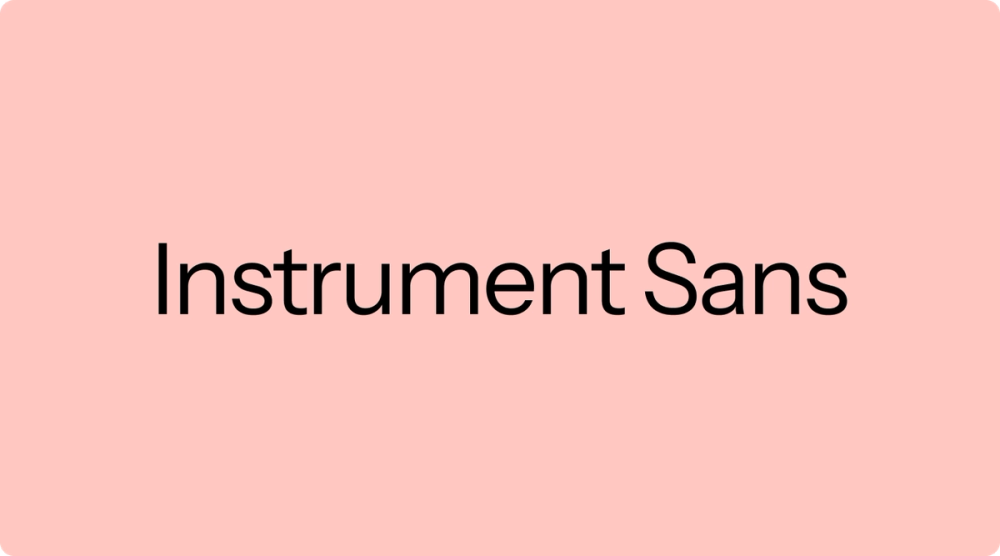
Tipo di font: sans serif
Instrument Sans è un font sans serif geometrico moderno con linee pulite e un design equilibrato. Porta un tono leggermente giocoso senza sacrificare la chiarezza, cosa che lo rende un'ottima scelta per i loghi che devono avere un aspetto attuale e trasmettere un senso di sicurezza.
Ideale per: startup tecnologiche, società di software e marchi moderni che desiderano un look elegante e professionale
Font 2: Instrument Serif
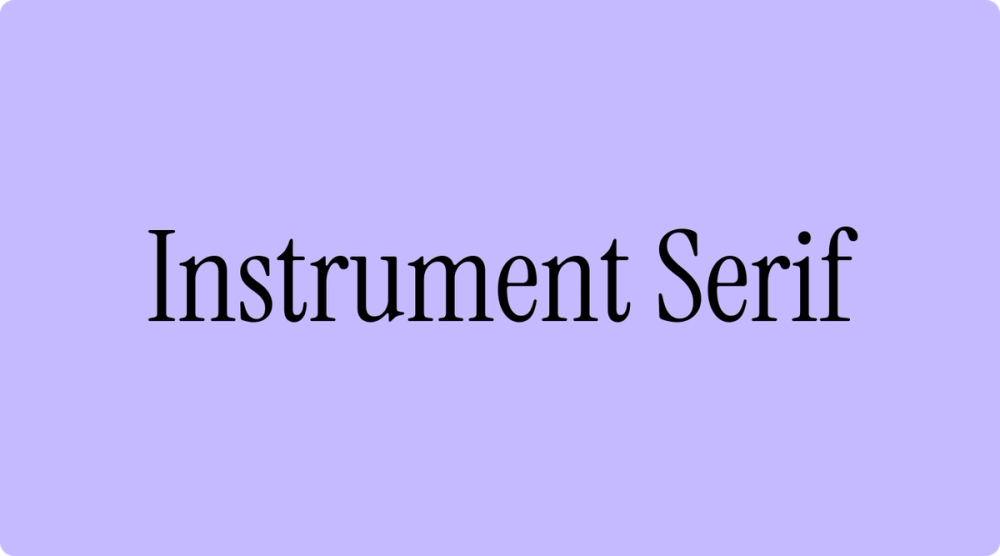
Tipo di font: serif
Instrument Serif unisce la classica struttura serif a un tocco raffinato e moderno. I suoi dettagli sottili aggiungono eleganza pur mantenendo un tono accessibile: l'ideale per i loghi che devono avere un look raffinato senza essere eccessivamente formali.
Ideale per: marchi di lusso, istituti finanziari e aziende di fascia alta che cercano di bilanciare raffinatezza e fascino informale
Font 3: Inclusive Sans
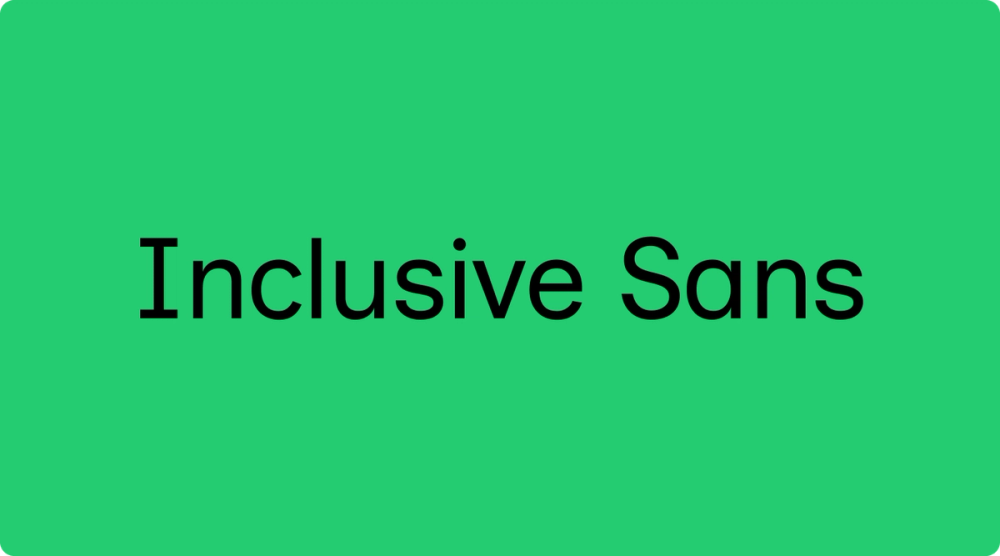
Tipo di font: sans serif
Inclusive Sans è stato progettato pensando all'accessibilità. Le sue forme aperte e la spaziatura generosa migliorano la leggibilità, rendendola una scelta affidabile per i loghi che danno priorità alla chiarezza e all'inclusione.
Ideale per:istituti scolastici, organizzazioni sanitarie, organizzazioni non profit e aziende che danno priorità all'inclusività e alla chiarezza
Font 4: Rethink Sans
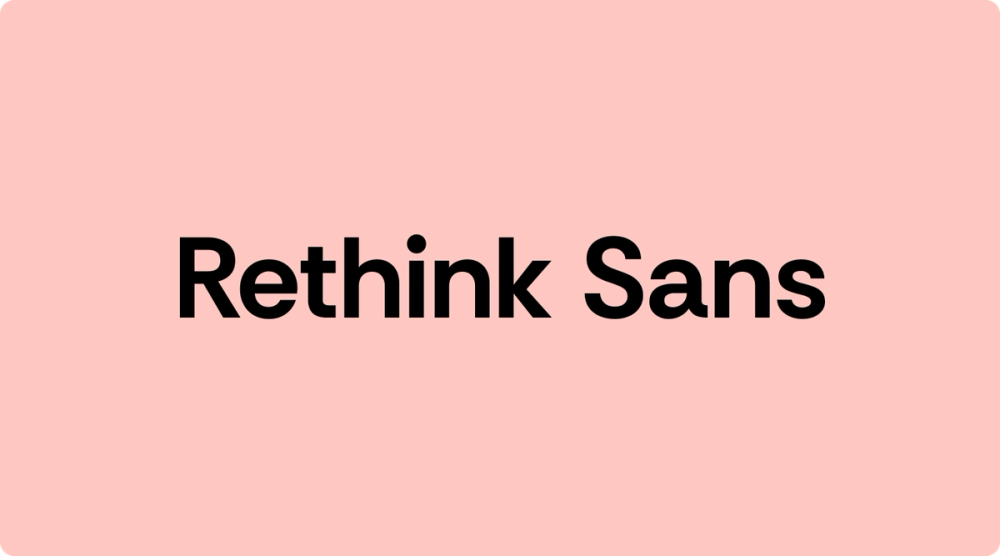
Tipo di font: sans serif
Rethink Sans trova un equilibrio tra audacia e semplicità, facendosi notare senza essere eccessivamente decorativo. Il suo design pulito e moderno lo rende ideale per i loghi che trasmettere un'immagine forte ma essere comunque accessibili.
Ideale per: agenzie creative, società di marketing e pubblicità, aziende tecnologiche e chi mira a una forte identità visiva pur mantenendo professionalità e calore
Font 5: Plus Jakarta Sans
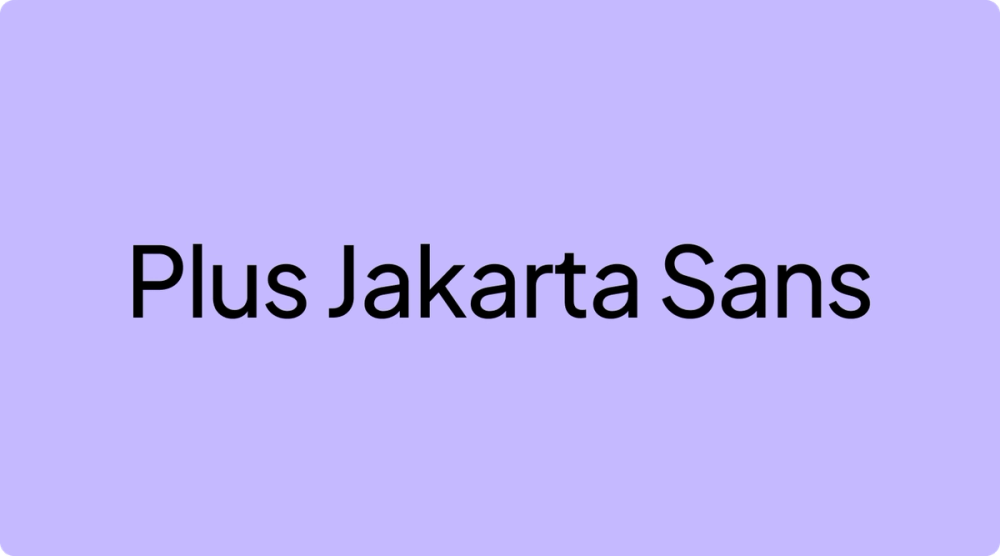
Tipo di font: sans serif
Plus Jakarta è un carattere tipografico sans serif geometrico con una struttura pulita e una personalità semplice. Il suo design moderno e le forme aperte delle lettere lo rendono un'ottima scelta per un branding professionale ma accessibile.
Ideale per: piattaforme di social media, aziende, prodotti digitali e startup che necessitano di un look moderno e riconoscibile
Font 6: Quintessential
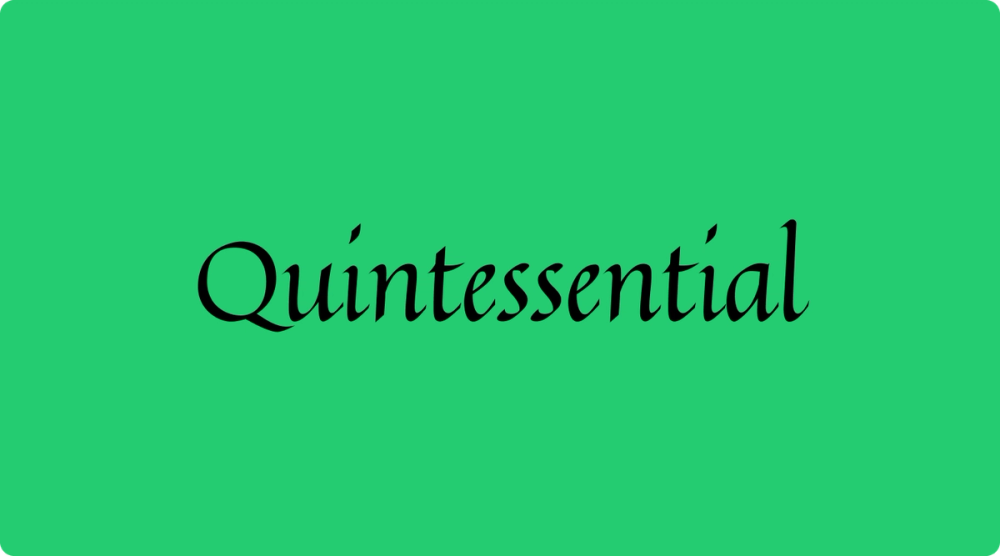
Tipo di font: script
Quintessential è un carattere decorativo dal sapore artigianale e nostalgico. Le sue lettere fluide e i dettagli unici aggiungono carattere e fascino, rendendolo un punto di riferimento per i marchi che desiderano un look espressivo e artistico.
Ideale per:marchi boutique, prodotti artigianali, caffè e aziende che vogliono trasmettere fascino e calore
Font 7: Work Sans
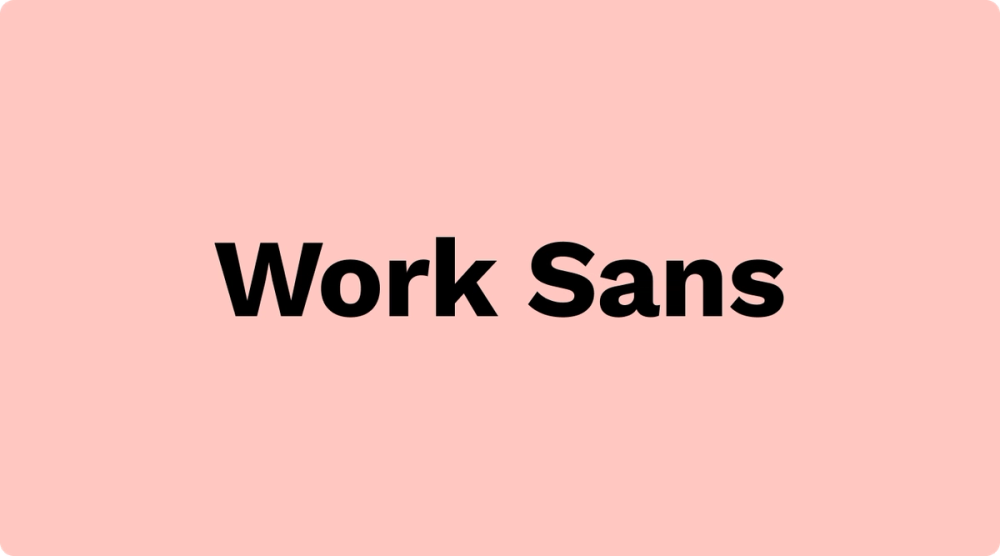
Tipo di font: sans serif
Work Sans è un font sans serif neutro e moderno noto per il suo equilibrio pulito e la sua versatilità. Le sue forme lineari lo rendono una scelta ideale per i loghi che devono avere un aspetto curato e pratico.
Ideale per: aziende tecnologiche, agenzie creative, società di software e sviluppo e aziende in generale che cercano uno stile di design affidabile e pulito
Font 8: Eczar
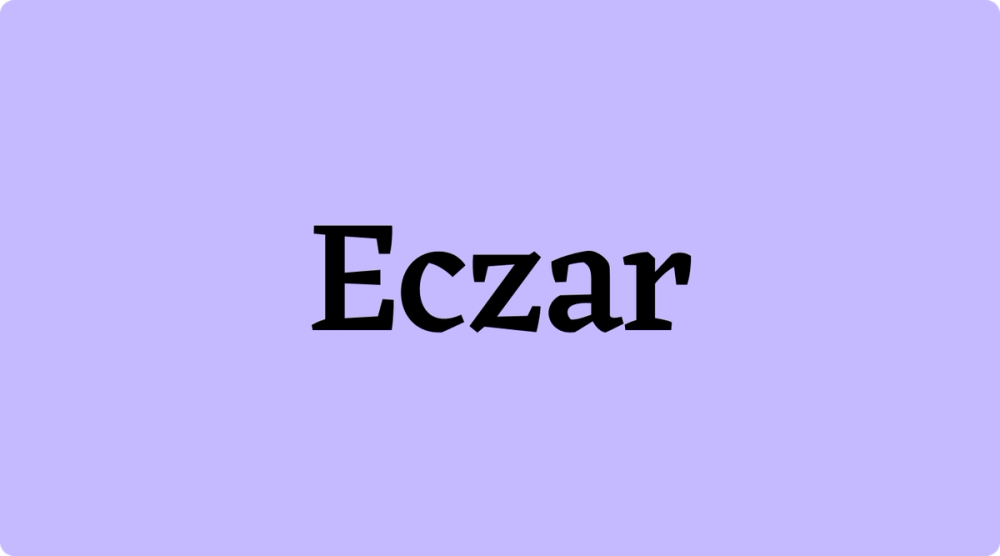
Tipo di font: display
Eczar è un font da visualizzazione in grassetto con serif nitidi e curve espressive. Progettato per avere un impatto su formati più grandi, conferisce struttura e presenza ai loghi con un tono raffinato.
Ideale per: istituti di istruzione, marchi dell'ospitalità di lusso e aziende che vogliono che il loro brand appaia raffinato e consolidato
Font 9: Prata
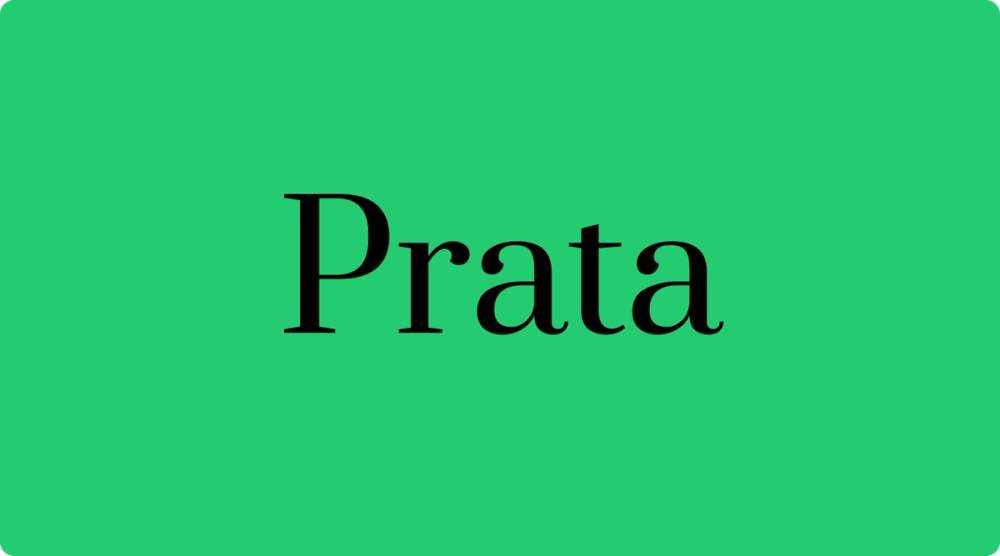
Tipo di font: display
Prata combina curve raffinate e tratti ad alto contrasto per un look senza tempo e contemporaneo. Grazie ai suoi tratti ad alto contrasto e alle curve raffinate, Prata è ideale per titoli di grandi dimensioni e loghi che devono avere un aspetto elegante senza essere troppo formali.
Ideale per: marchi di lusso che desiderano un'atmosfera senza tempo, come moda di alta gamma, gioielli e articoli di alta qualità
Font 10: Sniglet
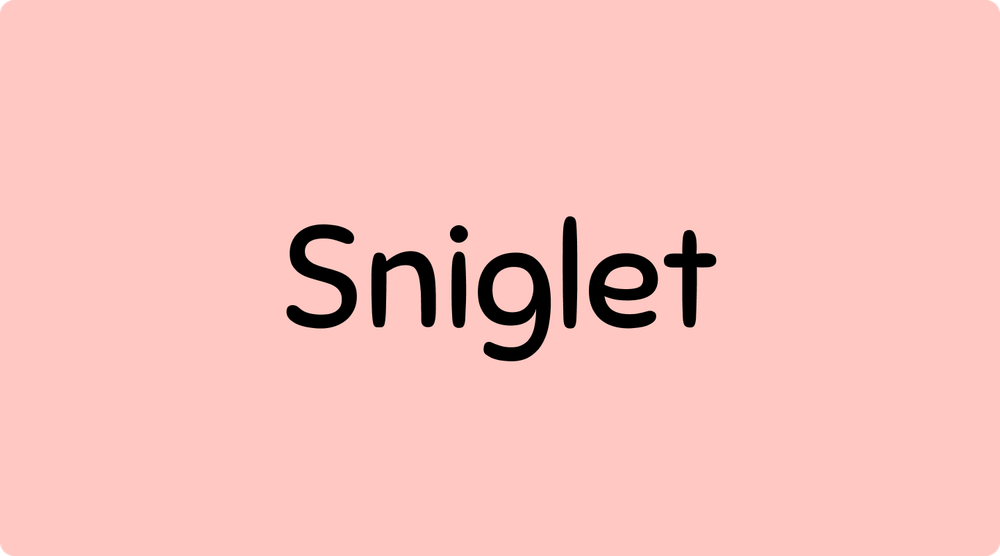
Tipo di font: display
Sniglet è un font arrotondato e pieno di personalità. Le sue forme vivaci e i bordi lisci conferiscono un tono spensierato, perfetto per un branding allegro e adatto alle famiglie.
Se desideri iniziare a progettare il logo perfetto, Figma può aiutarti. Ecco come:
Font che definiscono i marchi